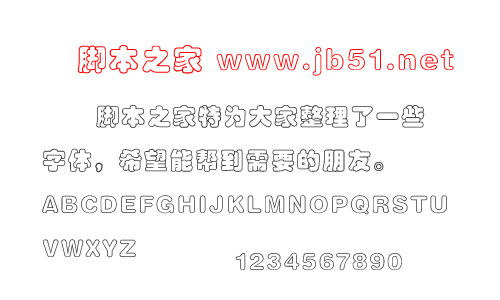
方正彩云简体字体
方正彩云简体字体是方正字体库中的一种字体,方正彩云的设计与方正琥珀的字形、笔形一致。这款字体的笔画是由黑线勾勒而成,笔画呈白色,并相互交叠,错落有序,如云朵飘浮,字形整体圆润轻盈。方正彩云的个性亲切可爱,珠圆玉润,适用于生活、儿童类品牌的广告和产品包装设计。喜欢的朋友们可以前来下载使用。